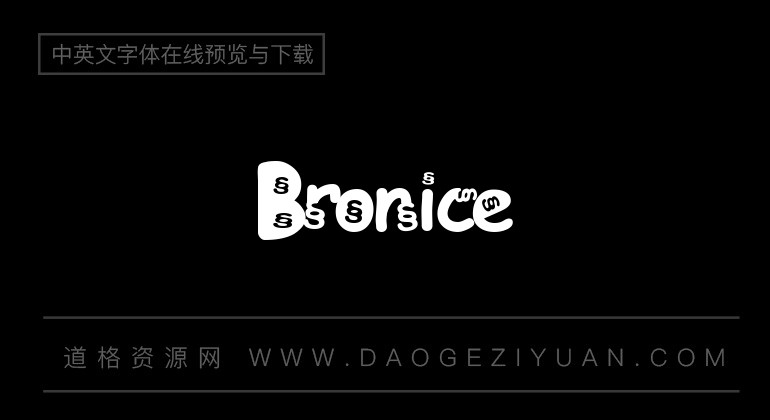
Bronice 字体是一款粗体英文字体,它的特点是简洁、粗犷、有力,适用于标题、标识、商标等场景。它的设计灵感来源于20世纪50年代的纽约街头涂鸦文化,结合现代技术,它具有出色的读写性能,可以提供更多的设计灵活性。它也可以用于印刷、网络、移动等多种媒体中,为品牌形象增添独特的设计风格。内容介绍
Bronice是一款非常不错的手写艺术字体,具有很好的视觉感,适合于文化类的宣传设计、商业类品牌的广告和产品包装设计以及个性化文字排版等较多场景。